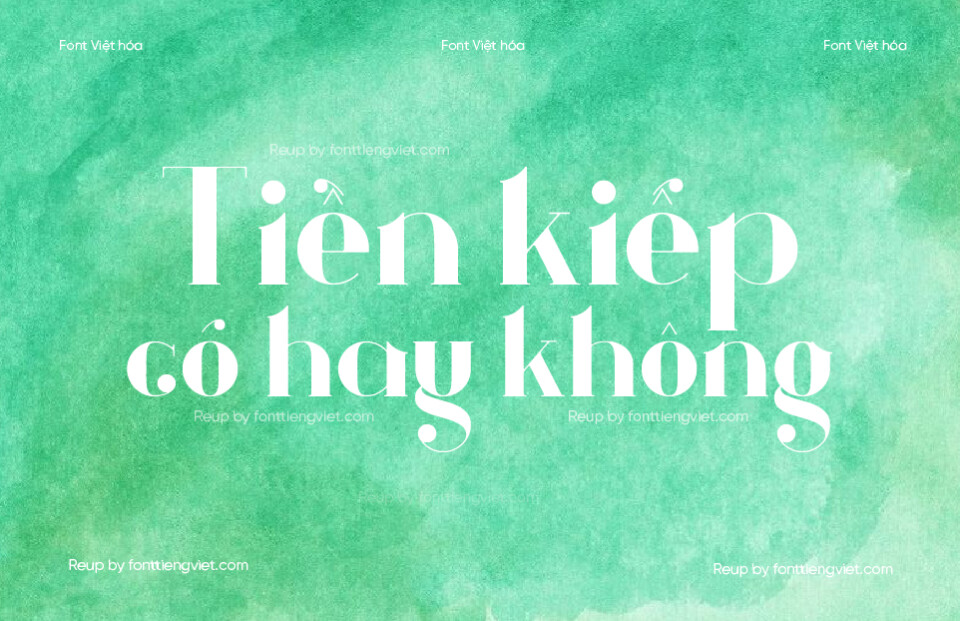
Font Việt hóa UTM Argo Old
Tải Ngay Font Việt hóa UTM Argo Old – Nét Đẹp Cổ Điển Cho Thiết Kế Giáo Dục
Trong thế giới thiết kế đồ họa, việc lựa chọn một bộ Font Miễn Phí phù hợp đóng vai trò quan trọng trong việc truyền tải thông điệp. Đặc biệt, với những dự án mang tính hoài cổ hoặc đòi hỏi sự trang trọng, Font Việt hóa UTM Argo Old chính là sự lựa chọn hàng đầu. Đây là một phông chữ được tinh chỉnh kỹ lưỡng, giúp các bạn học sinh và thầy cô dễ dàng tạo ra những tài liệu học tập đẹp mắt, ấn tượng mà không lo lỗi font tiếng Việt.
Đặc điểm nổi bật của Font Việt hóa UTM Argo Old
Bộ phông này thuộc dòng Serif (có chân) với các đường nét mạnh mẽ nhưng không kém phần uyển chuyển. Cấu trúc chữ được thiết kế cân đối, mang đậm hơi thở của những bản in cổ điển thế kỷ trước. Khi sử dụng Font Việt hóa UTM Argo Old, các văn bản của bạn sẽ trở nên chuyên nghiệp và có chiều sâu nghệ thuật hơn rất nhiều.
Ứng dụng trong môi trường học đường
Nhờ tính thẩm mỹ cao, phông chữ này thường được các bạn học sinh dùng để thiết kế bìa báo tường, thiệp chúc mừng thầy cô hoặc các bài thuyết trình lịch sử. Độ tương phản giữa các nét thanh và nét đậm giúp chữ cực kỳ dễ đọc trên cả màn hình máy tính lẫn giấy in.